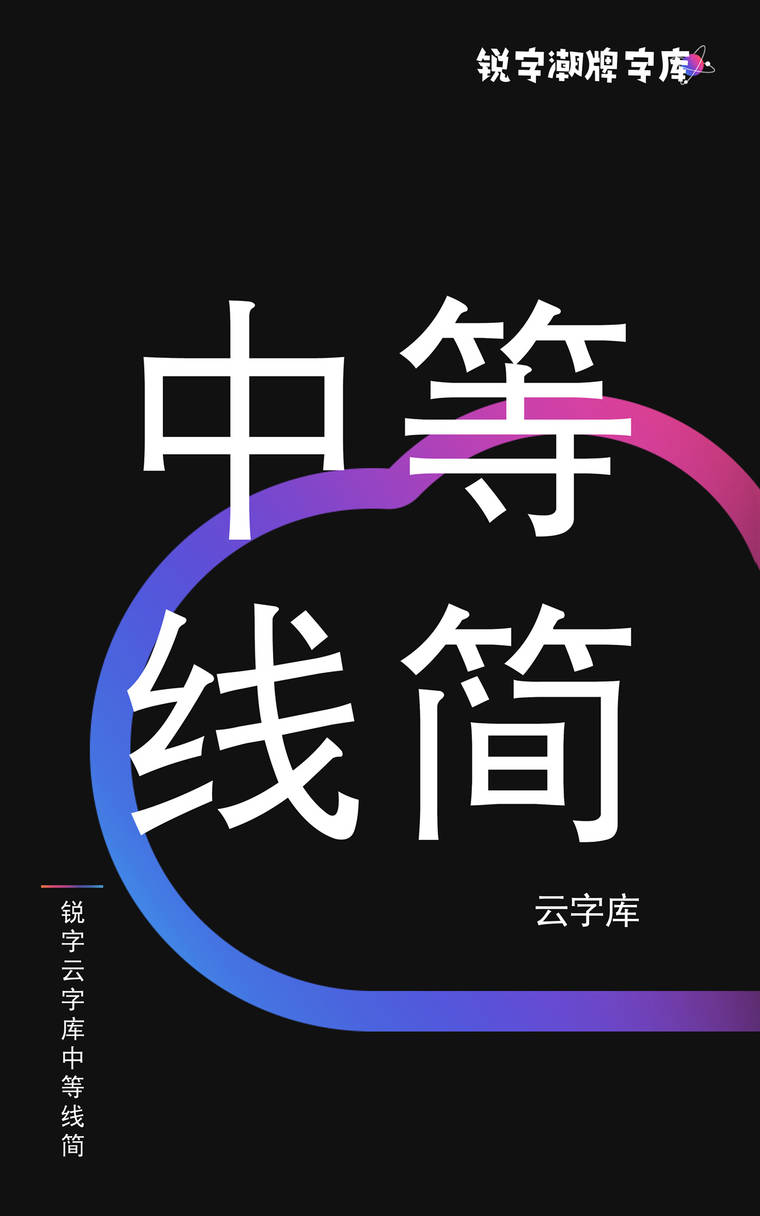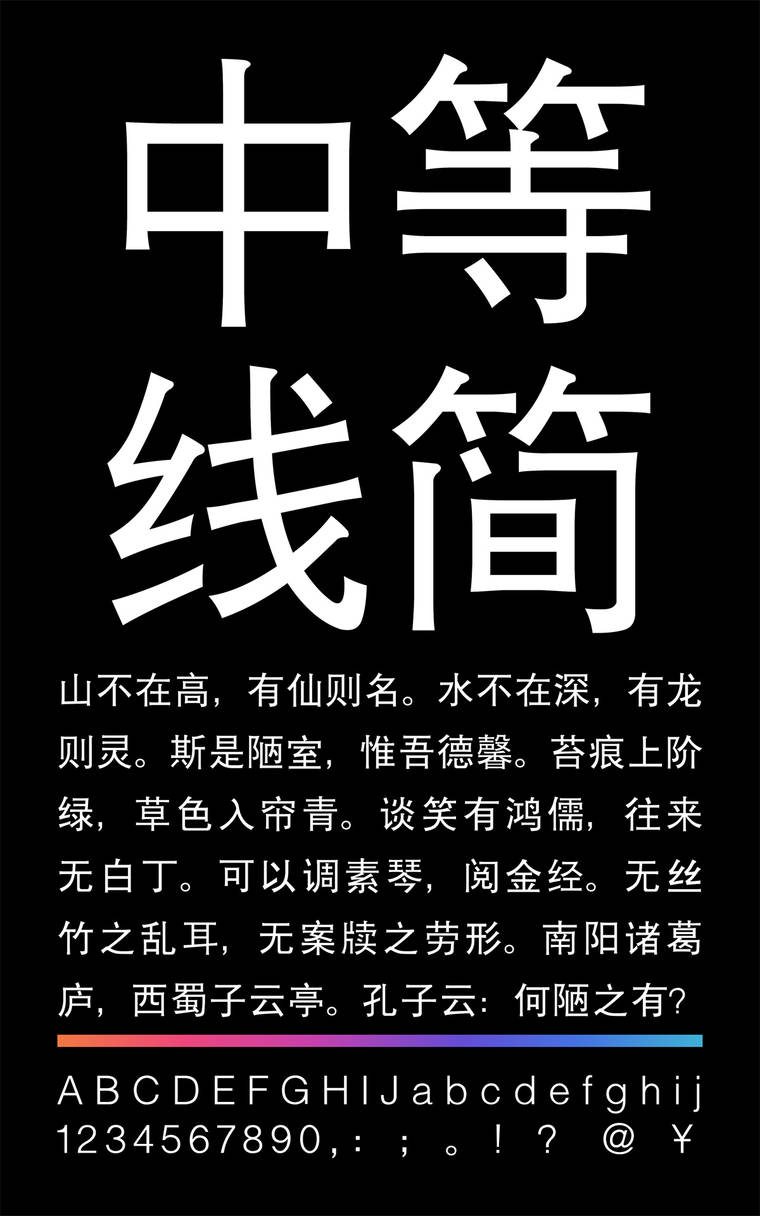
锐字云字库中等线简
锐字云字库中等线简字体介绍
锐字云字库中等线简,是云字库品牌字库旗下的一款字体。锐字潮牌字库拥有本字体独家版权,并提供锐字云字库中等线简的官方免费下载服务。
字体特征:特点是撇捺等笔画不尖,字形端庄,笔画横平竖直,笔迹全部一样粗细,结构醒目严密。方正、朴素、简洁、无装饰、横竖笔形粗细视觉相等,笔形方头方尾、黑白均匀,因此非常醒目,运用广泛。